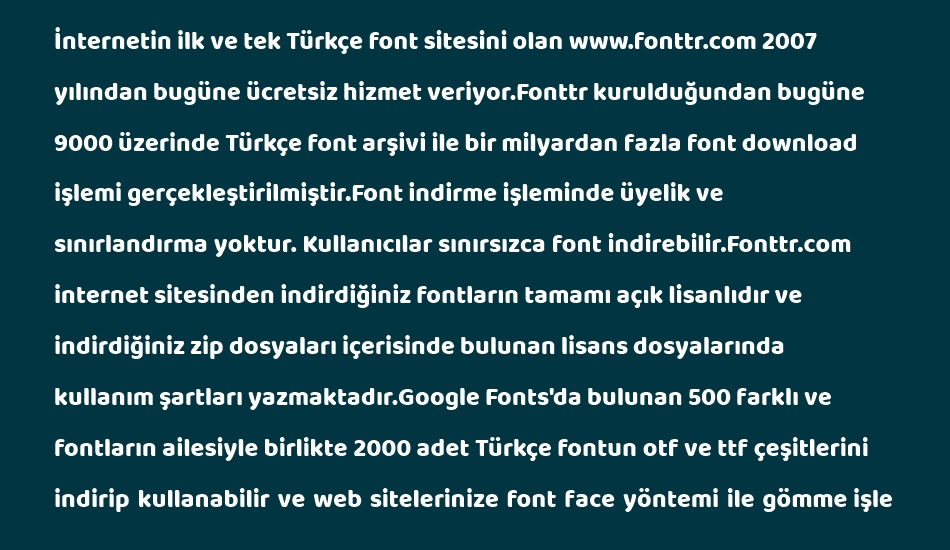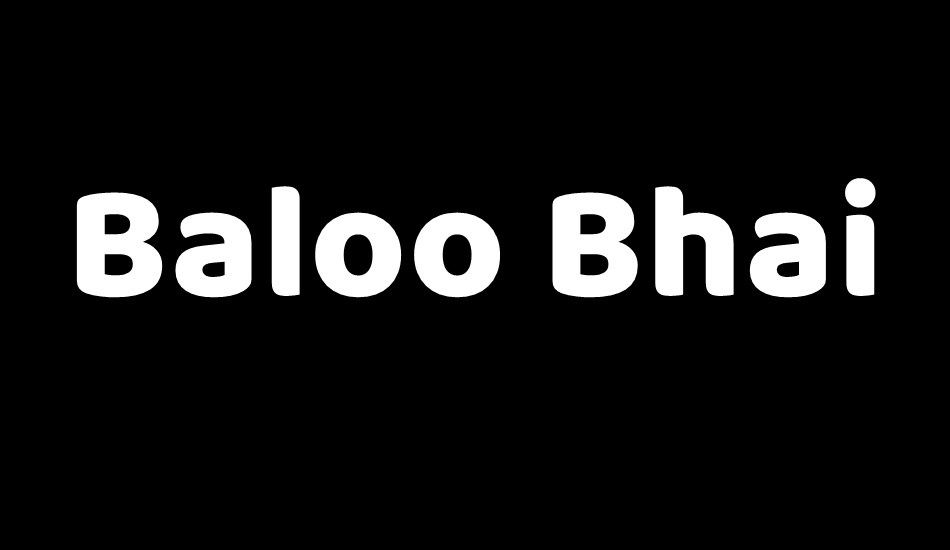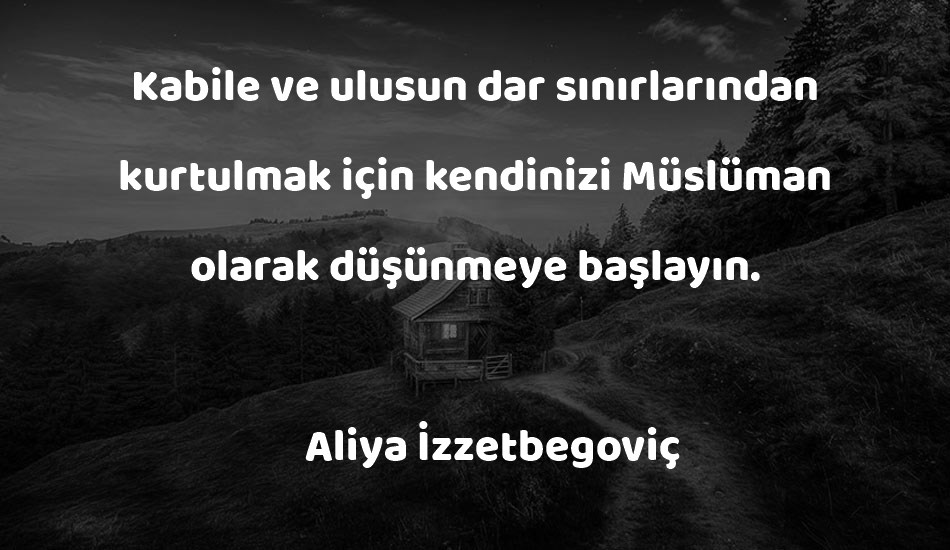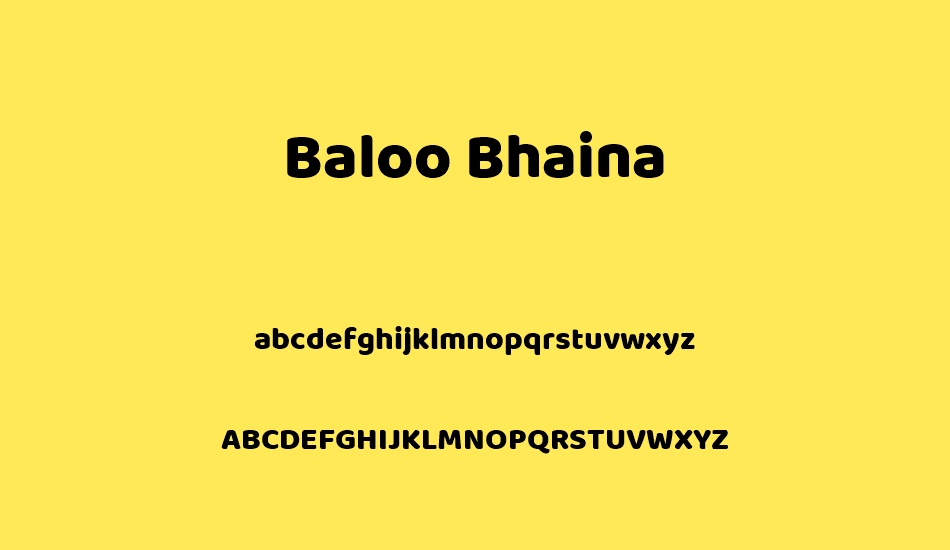
Baloo Bhaina font
Bir kürk katında sivri pençelerin mükemmel bir karışımı olan Baloo, Ek Type'ın kullanışlı bir ekran yazı biçimidir. Dokuz Hintli senaryonun yanı sıra Latin muadili ile de mevcut olan aileler Unicode'a uyumlu ve libre lisanslıdır.
Baloo font , şaşkınlığın ince bir tonuyla ve çıplak ihtiyaçları olan farklı, ağır bir spurless tasarımdır. Tek bir ağırlıkta birkaç betik doldurmak için yazım biçimi, tekli ve çoklu komut dosyalarının kullanımını güvence altına almak için bu nazik ormancılık meselesinin her hareketine eşit adalet vermeye odaklanır. Umutsuz ama kendinden emin, sıcak ancak eğlenceli, cömert ve anlaşılır olan Baloo, her yere giderken her yere can verir.
Baloo projesi dokuz İndik Komut Dosyası'nın her biri için benzersiz yerel adlarla dokuz ayrı yazı tipi geliştirir. Her yazı tipi, bir Hint alt grubuna artı Latin, Latin Genişletilmiş ve Vietnamca'yı destekler.
İyi yazılmış ve her senaryoya özen gösterilmiş, Baloo'yu arıtmak için kararlı bir tip tasarımcılardan oluşan bir ekip taşıdı ve sevdiğimiz yazı karakteri olarak yükseltti. Baloo'nun Devanagari Sarang Kulkarni, Manish Minz ve Shuchita Grover, Maithili Shingre ve Tamilce tarafından Omkar Shende, Malayalam tarafından Divya Kowshik, Telugu tarafından Supriya Tembe ve Noopur Datye, Kannada tarafından Gujarati tarafından Noopur Datye, Oriya tarafından Shuchita Grover, Bangla tarafından Gurmukhi tarafından tasarlanmıştır Aadarsh ??Rajan. Baloo Latin, Ek Type tarafından ortak olarak tasarlanmıştır. Girish Dalvi tarafından tasarım yardımı ve yazı tipi mühendisliği yazın.